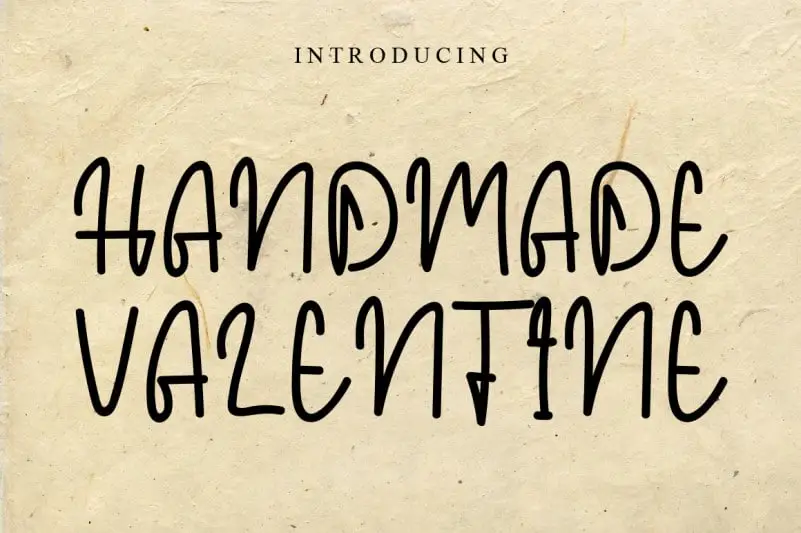
A fonte ‘Handmade Valentine Font’ traz uma atmosfera envolventemente romântica e natural perfeita para quem busca criar designs emocionantes e únicos. Com um estilo fresco e única, ela se assemelha a letras escritas à mão, adicionando uma personalidade amigável aos seus projetos. Seu nome sugere uma fonte de amor, mas é sua natureza livre que torna-a uma escolha inteligente para um leque amplo de designs. Sua característica principal é o seu estilo natural e único, que não só se encaixa em diversos projetos, desde cartões de aniversário até logos pessoais, como também permite ao criador explorar sua imaginação sem limites. Se você está à procura de uma fonte para criar algo especial e autêntico, essa é a escolha certa.